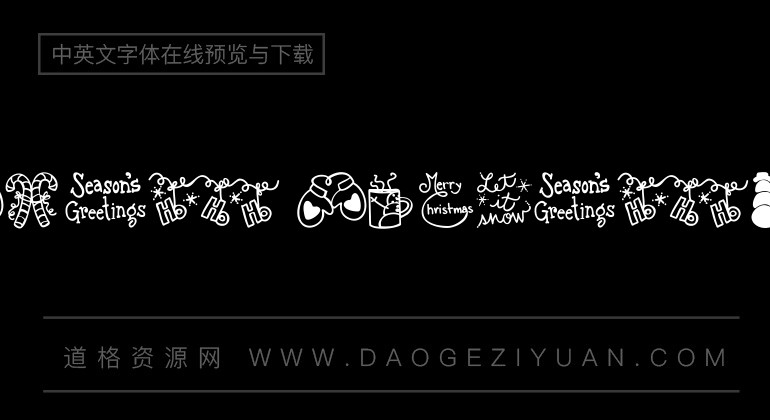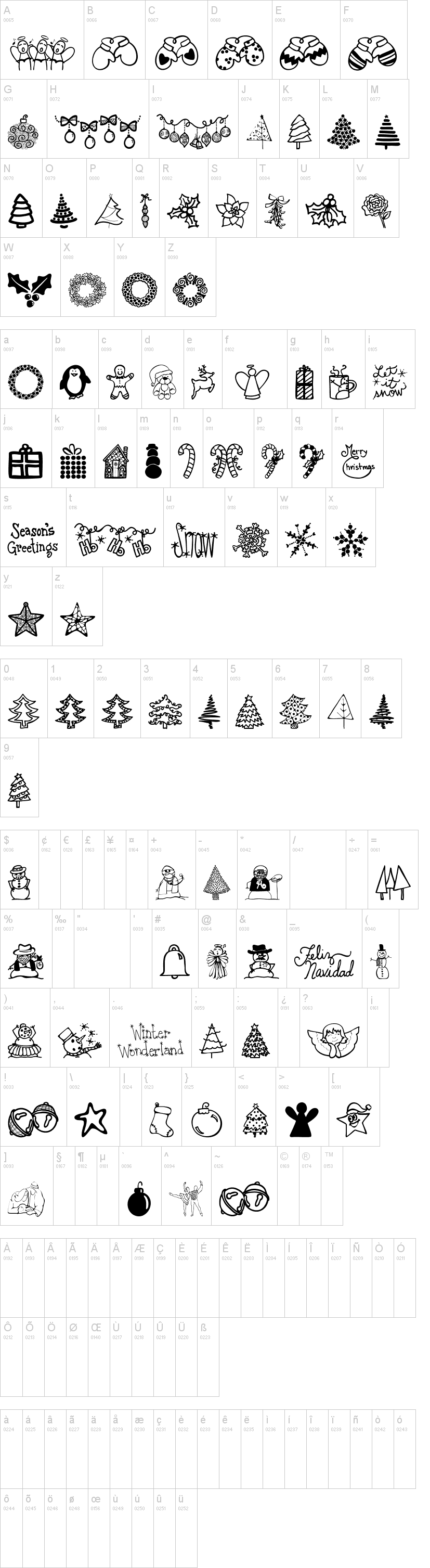
Austie Bost Christmas Doodles
Austie Bost Christmas Doodles是一款由Austie Bost字体公司出品的垂直节日字体,它是一款具有欢乐气氛的节日字体,采用简约的线条构成,在细节上设计十分精致,充满童趣的节日气氛,可以用于制作节日卡片、婚礼邀请函、宣传海报等等,是一款非常适合用于节日场景的字体。
Austie Bost Christmas Doodles是一款非常不错的手写艺术字体,具有很好的视觉感,适合于文化类的宣传设计、商业类品牌的广告和产品包装设计以及个性化文字排版等较多场景。
Austie Bost Christmas Doodles字符映射图